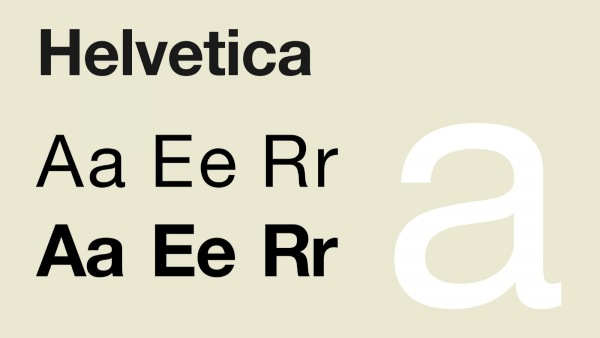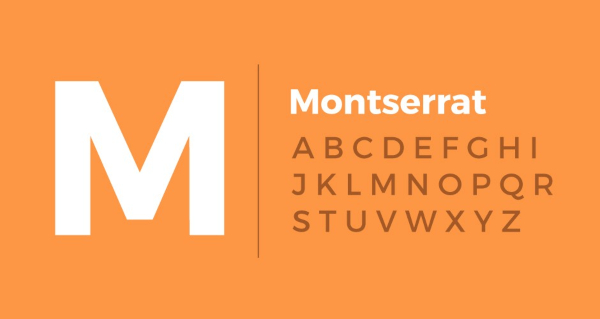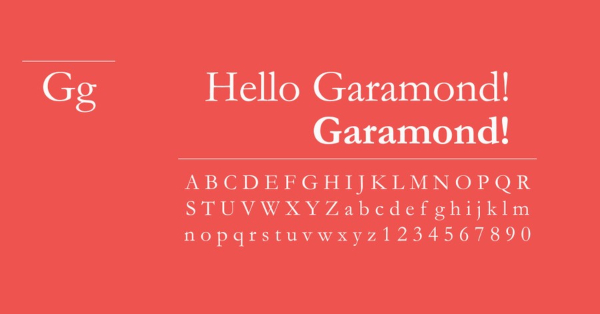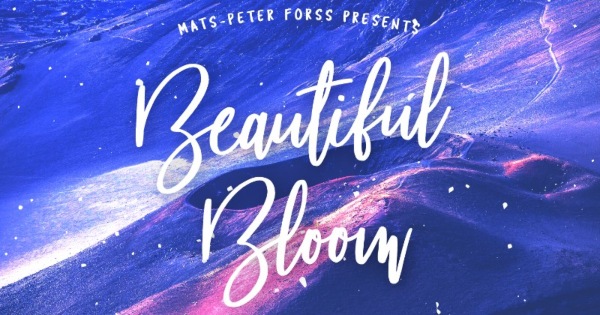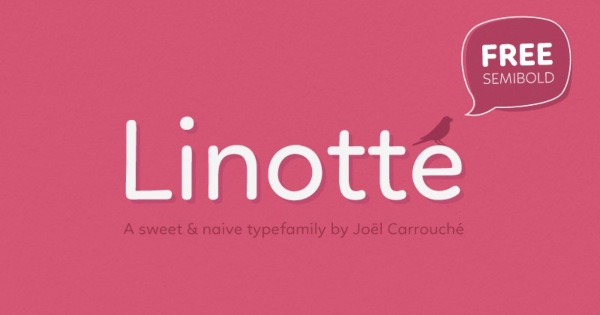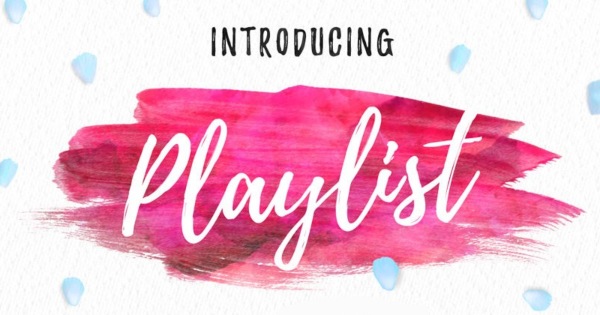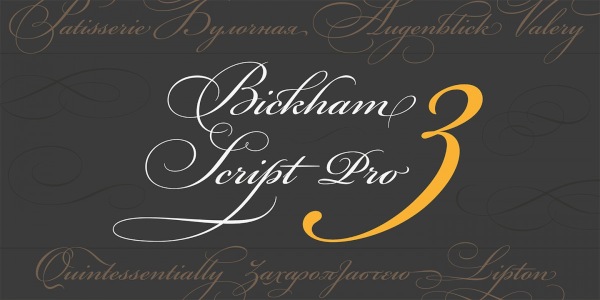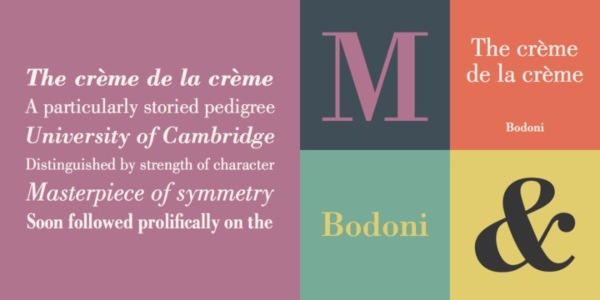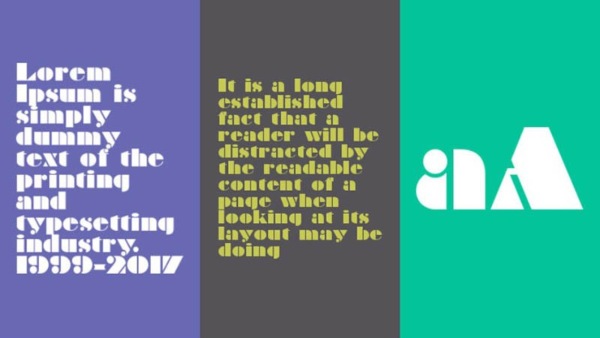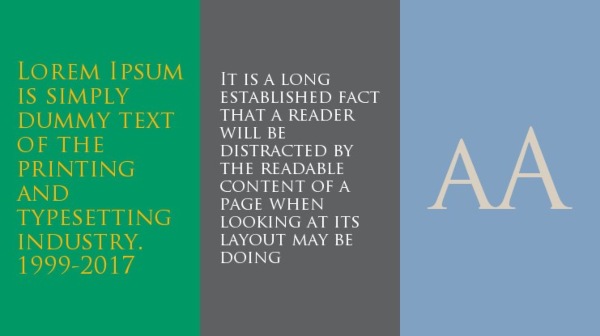
TOP 15+ font chữ đẹp Việt hóa dành riêng cho thiết kế
Bạn là người mới học thiết kế, bạn đang muốn tìm hiểu những font chữ cho thiết kế của mình. Vậy thì hãy cùng Unica đi tìm hiểu 15+ font chữ đẹp cho thiết kế và sáng tạo dành cho bạn nhé! Đặc biệt đây đều là những font chữ đẹp Photoshop Việt Hóa rồi nên bạn có thể dùng được ngay.
Font Helvetica
Helvetica là một trong những font chữ đẹp nhất hiện nay được rất nhiều người - không chỉ riêng thiết kế - ưu ái lựa chọn chúng. Thuộc nhóm chữ không chân San Serifs, font Helvetica đã thể hiện được tinh thần rất tốt của các phông chữ không chân: mạnh mẽ, đơn giản, dễ đọc và phù hợp với hầu hết các thể loại, tác phẩm, sản phẩm thiết kế hay báo chí. Tuy rằng font chữ này bị khá nhiều nhà thiết kế chuyên về Typo loại trừ vì thiếu sáng tạo, bay bổng nhẹ nhàng, thế nhưng đây vẫn là sự lựa chọn của rất nhiều nhà thiết kế chuyên nghiệp và không chuyên khác.
Font chữ thiết kế San Serifs Helvetica
Font Montserrat
Font chữ kiểu Montserrat cũng là một phông chữ được rất nhiều nhà thiết kế ưa chuộng bởi chúng gần giống với phông không chân Helvetica nhưng nét dày hơn, đều và đậm hơn. Chúng xuất hiện nhiều trong các ứng dụng di động hoặc website, blog... Nhưng nhiều người đánh giá phông chữ này không hợp để trình bày nội dung dài.
Font chữ San Serifs Montserrat
Font Garamond
Font chữ Garamond việt hóa là một lựa chọn tuyệt vời của rất nhiều tạp chí, website hay những văn bản có nội dung dài. Chúng được coi là font chữ dễ đọc nhất, đơn giản và phù hợp nhất sau Helvetica. Đây cũng là bộ hai font chữ đẹp cho Photoshop, khi mà font chữ photoshop này được sử dụng nhiều nhất ở phiên bản  Adobe ITC Garamond (1989).
Phông chữ có chân Garamond
Font Beautiful Bloom
Đây là một font chữ nghệ thuật cũng rất được sử dụng nhiều trong các quảng cáo hoặc poster, banner, theo phong cách viết tay hoặc phong cách thư pháp. Và font chữ Beautiful Bloom chính là sự kết hợp hoàn hảo để bạn có thể làm nổi bật hơn những tác phẩm thiết kế của mình. Bạn sẽ thấy font chữ này nhiều trong các thiết kế yêu cầu sự mềm mại, nhẹ nhàng như thư mời, thư cảm ơn hoặc banner quảng cáo.
Font chữ thiết kế poster Beautiful Bloom
Font Linotte
Linote là font chữ khá mềm, các nét giao của viền chữ được bo tròn tạo cảm giác dễ gần, vui vẻ, rất phù hợp với các thiết kế yêu cầu sự vui vẻ hạnh phúc đó.
Phông chữ đẹp Linotte
Font Playlist
Khi sử dụng font chữ này bạn sẽ nhận thấy phông chữ này có kết hợp với một nét khác, gần giống như một nét cọ khô lỏng được tô theo khi di chuyển bút. Font chữ số đẹp này là phiên bản sans của chữ tay kết hợp với nét cọ khô đó, gây cảm giác chân thật hơn cho chữ của bạn.
Phông chữ Playlist
Font Futura
Khi nhìn vào font chữ này bạn sẽ cảm nhận được sự cứng cáp, mạnh mẽ, đồng đều và tạo cảm giác an tâm hơn các kiểu khác. Các nét trên chữ cũng khá phù hợp để trình bày nội dung dài.
Phông chữ hiện đại Futura
Font Bickham Script Pro
Các nét chữ trong font Bickham Script Pro thường khá điệu đà bóng bẩy, nó được dùng nhiều trong các sản phẩm thiết kế mang hơi thở sang trọng như thư mời, thiệp mời...
Phông chữ hiện đại Bickham Script Pro
Font Bodoni
Bodoni nằm trong nhóm chữ Modern Serif, tức nhóm chữ dài, có chân, trục mảnh và gần như đứng thẳng. Font chữ đẹp này có độ tương phản, độ rộng của chữ và nổi bật khá cao so với các font khác.
Phông chữ Modern Serif Bodoni
Font Edwardian Script ITC
Đây là một font chữ bóng bẩy, bay bổng và nhiều nét mềm mại, dễ dàng đem đến cho người xem cảm giác nhẹ nhàng, bay bổng hạnh phúc theo. Loại phông chữ này xuất hiện nhiều trong các thiệp đám cưới, thiệp mời hay ăn tân gia, những dịp vui vẻ, trọng đại. Và thông thường font chữ này được dùng để làm tiêu đề trang trí nhiều hơn là trình bày nội dung văn bản bởi chúng dễ gây rối mắt.
Phông chữ Modern Serif Bodoni
Font Braggadocio
Cũng cùng nằm trong nhóm font chữ không chân như  Helvetica, nhưng font chữ đẹp Braggadocio mang đậm hơi thở cổ điển, siêu cách điệu và rất táo bạo, do đó nó được dùng nhiều để làm tựa đề cho các sản phẩm thiết kế như banner, retro. Cũng bởi vì chúng cách điệu quá nhiều, nên thường không được ứng dụng để trình bày nội dung - ngược lại với Helvetica.
Phông chữ nhóm Sans Serifs Braggadocio
Font Trajan
Nếu là một người hay để ý nhiều có lẽ bạn sẽ nhận ra font chữ kiểu này rất hay xuất hiện tại các bộ phim của Hollywood. Thuộc nhóm font chữ không chân Sans Serifs cổ điển và được lấy cảm hứng từ các con số La Mã những năm 1989. Và đây là font chữ đầu tiên được thiết kế cho Adobe đấy.
Phông chữ nhóm Sans Serifs Trajan
>>> Xem ngay: Top 5 Font chữ viết tay Việt hóa cho người làm thiết kế
Trở thành chuyên gia powerpoint bằng cách đăng ký học online qua video ngay. Khóa học sẽ giúp bạn biết thiết kế hình ảnh và khởi tạo video chuyên nghiệp mà không cần dùng đến các phần mềm chuyên sâu như Photoshop, Illustrator… Đặc biệt, bạn sẽ có thể vận dụng linh hoạt các yếu tố: hình ảnh, ngôn ngữ, đồ họa 2D - 3D, audio, hiệu ứng, ảnh động để tạo nên một bản Powerpoint hoàn chỉnh nhất.
[course_id:543,theme:course]
[course_id:53,theme:course]
[course_id:1630,theme:course]
Font American Typewriter
Font chữ đẹp American Typewriter được đánh giá là gần giống với font chữ Time New Roman rất thường thấy trong văn bản của Việt Nam nhưng mang hơi thở hiện đại hơn, đơn giản và đều nét hơn chút. Nó sẽ đặc biệt phù hợp với các sản phẩm thiết kế phong cách Retro hay trình bày văn bản ngày xưa.
Phông chữ American Typewriter
Font Cabana
Còn nếu bạn đang muốn thiết kế của mình có phong cách  mới mẻ, sáng tạo và ấn tượng ngay từ cái nhìn đầu tiên? Bạn rất nên thử phông chữ Cabana đấy! Đặc trưng của phông chữ này có dáng cao, không cứng cáp mà khá mềm.
Phông chữ Cabana
Font Times New Roman
Dĩ nhiên rồi, Times New Roman dù thế nào đi chăng nữa vẫn là font chữ mềm mại Việt hóa được nhiều nhà thiết kế Việt Nam lựa chọn nhất để trình bày nội dung của mình. Không quá hào nhoáng, không quá cầu kỳ nhưng vẫn đảm bảo tính thẩm mỹ cao, đây chính là font chữ dễ đọc nhất được sử dụng nhiều nhất, ít nhất là ở Việt Nam chúng ta hiện nay.
Phông chữ Times New Roman
Kết luận
Hi vọng với 15 gợi ý font chữ đẹp này, bạn đã có thể lựa chọn được cho mình một phông chữ số đẹp để thiết kế hoàn chỉnh những tác phẩm sáng tạo của bạn.